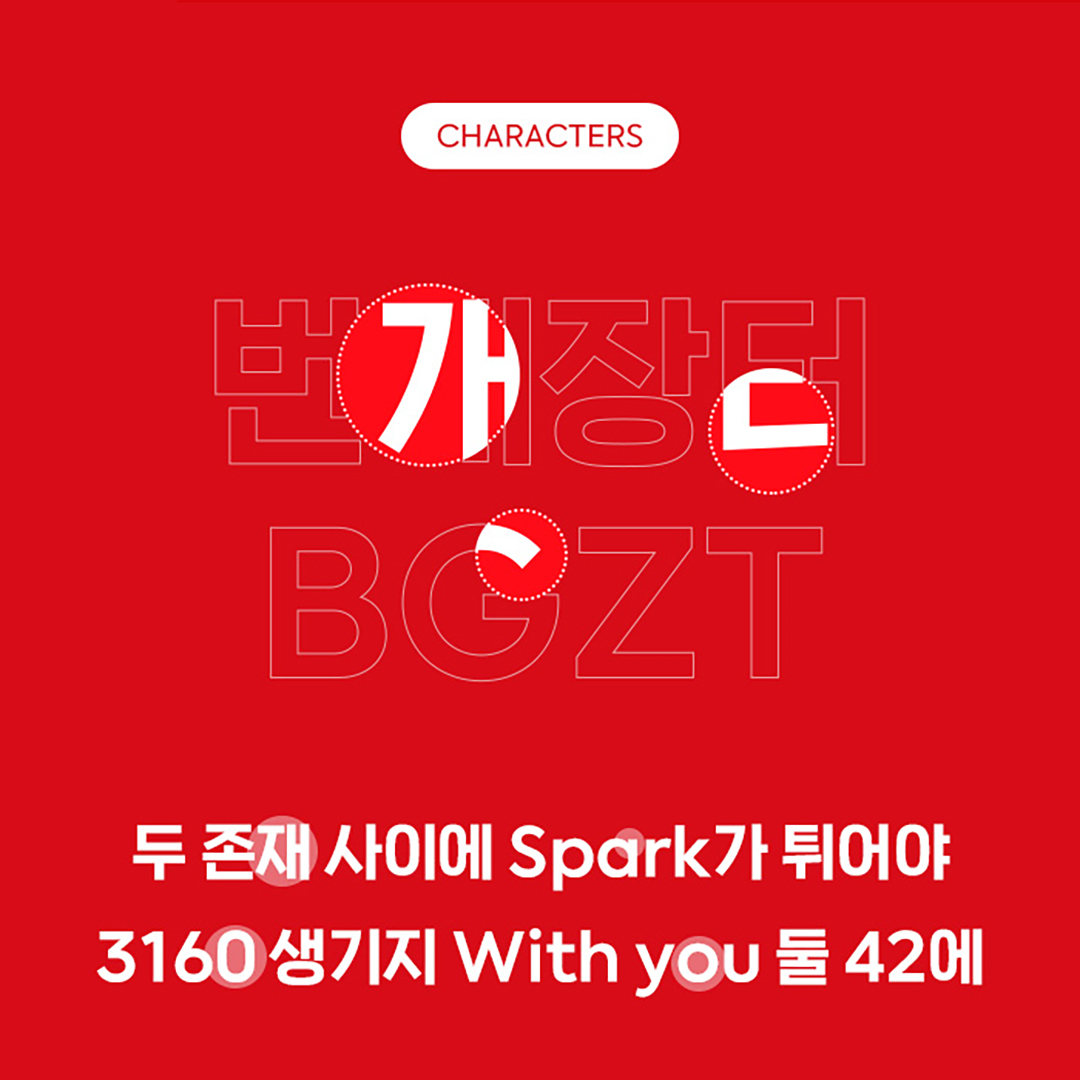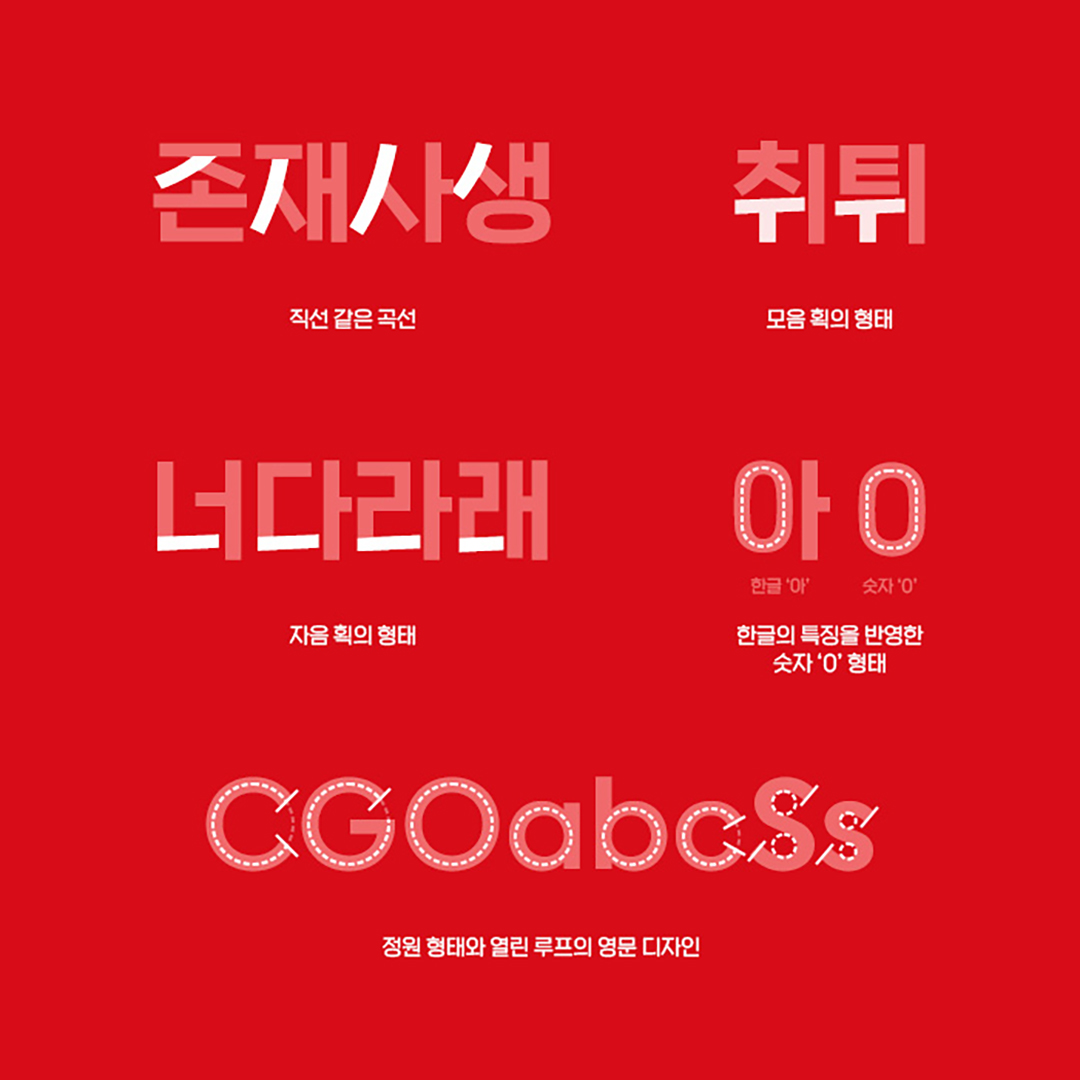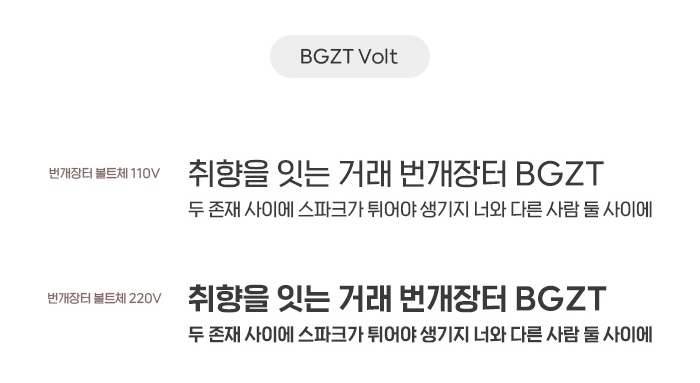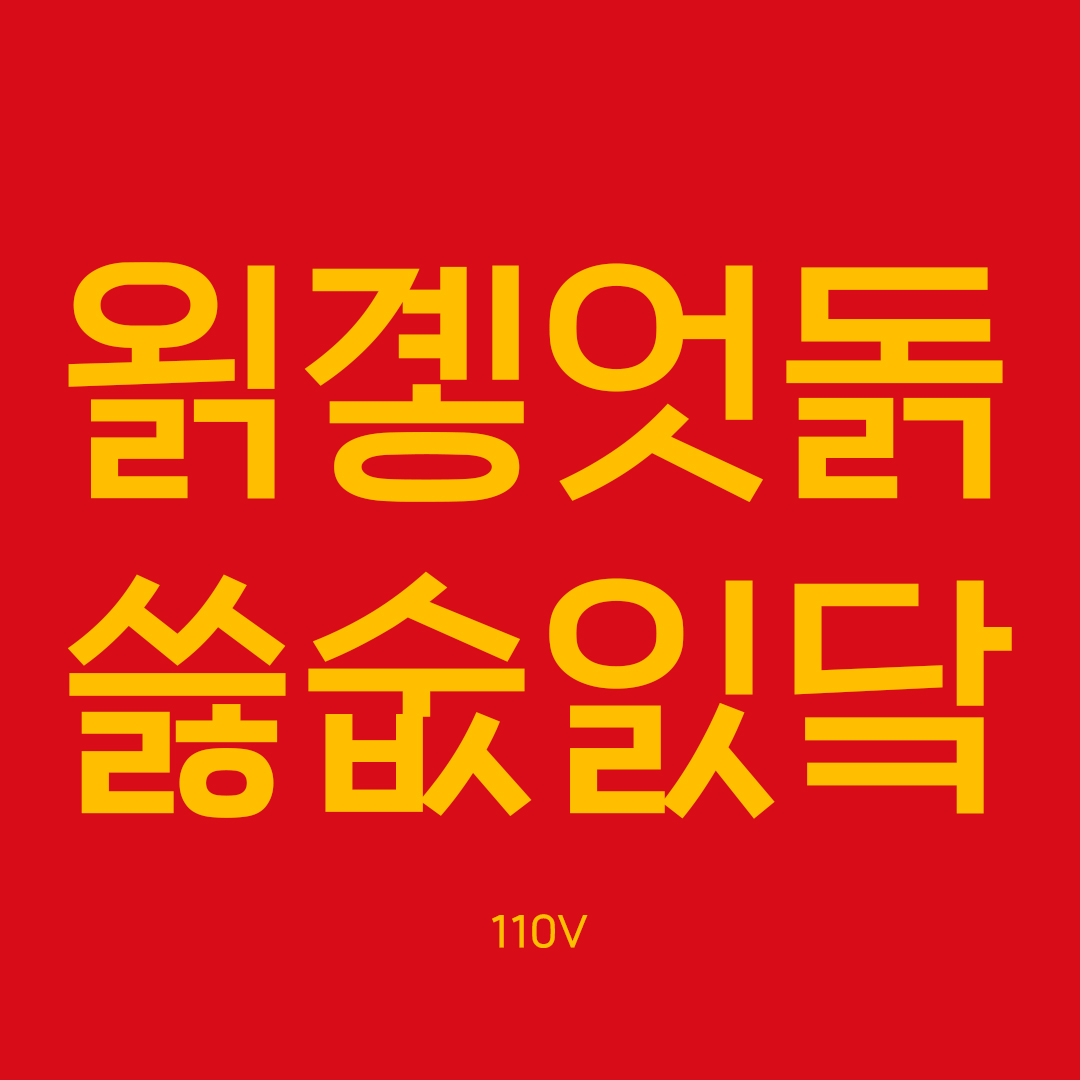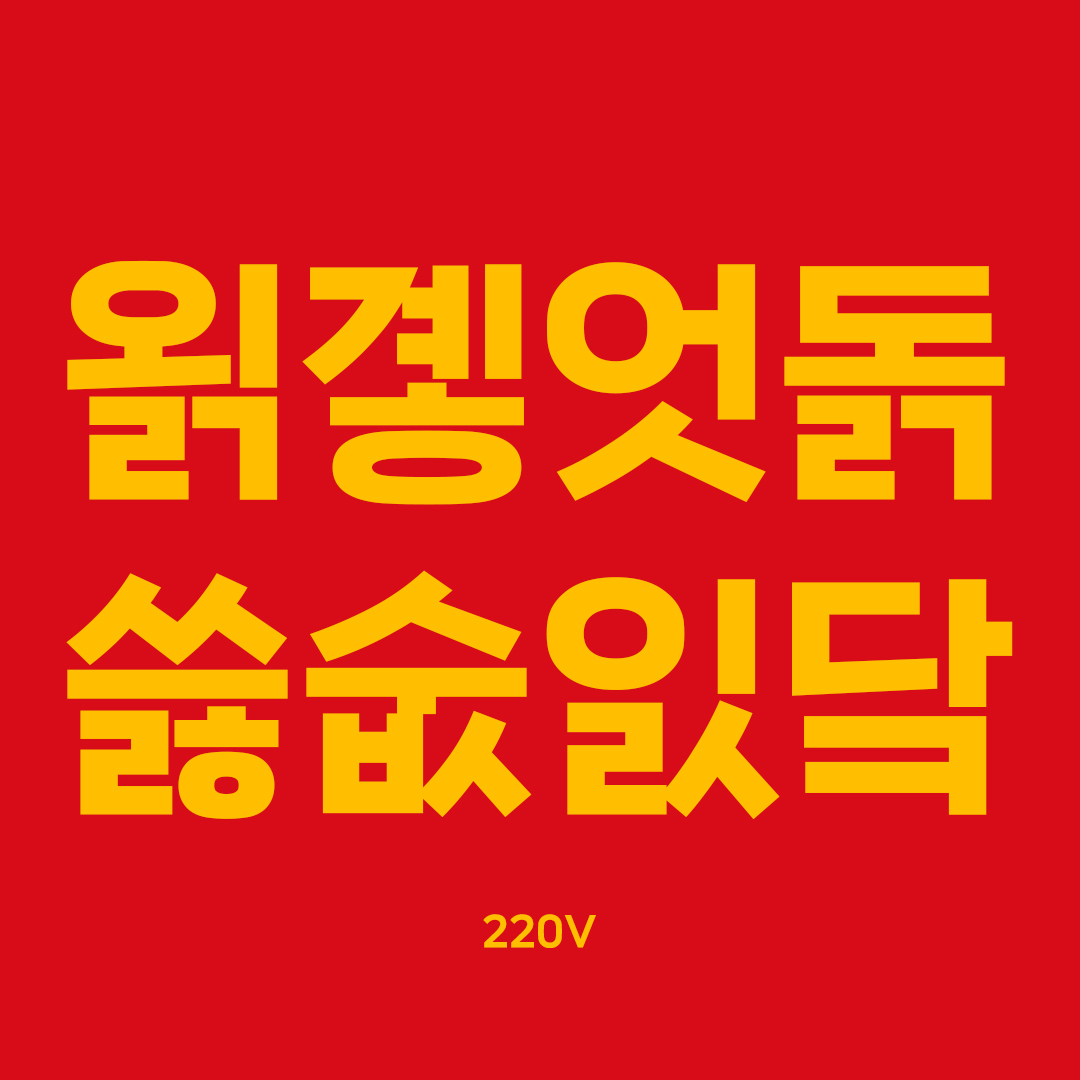
안녕하세요. 오늘은 대표적인 중고거래 플랫폼 중 하나인 번개장터의 전용서체 「볼트체」를 소개해 드려요! 서체명부터 전기가 찌릿찌릿 강렬한 개성 넘치는 서체가 탄생한 느낌이 드는데요. 취향을 기반으로 하는 안전한 중고거래 플랫폼에 대한 비전을 담아 제작한 번개장터 볼트체에 대해 자세히 알아볼게요!
#1 취향의 스파크가 튀는 볼트체 ⚡
전용서체 제작 시 가장 중요한 작업 중 하나가 바로 기업의 이미지와 아이덴티티를 담는 것인데요. 기업의 브랜딩에 큰 역할을 하는 서체 개발인 만큼 많은 커뮤니케이션과 연구가 필요한 부분이죠. 번개장터는 중고거래 플랫폼으로 독특하게 취향에 대한 이야기를 하는 브랜드예요. 서로 다른 두 가지의 취향이 만나 스파크가 튀어야 거래가 이뤄질 수 있다는 의미를 담은 새로운 로고에 맞춰 볼트체를 개발했습니다.
번개장터의 번개같이 빠른 거래, 취향의 스파크 등 키워드를 녹여내기 위해 주로 직선적인 요소를 많이 사용하여 시원한 분위기의 트렌디한 디자인의 서체를 제작했습니다. 꽉 찬 네모꼴 형태에 단단하고 안정감을 주는 구조로 빠르지만 안전한 중고거래 플랫폼의 이미지를 담았습니다. 한글의 특징을 반영하여 함께 사용할 때 조화로운 영문, 숫자, 심볼 등의 디자인도 신경 써서 제작했습니다.
#2 위트와 재미를 담은 폰트
위트 있고 자신감 넘치는 번개장터의 성격을 담은 볼트체라는 이름에 맞게 두께 표기도 좀 더 특별하게 했는데요🔌 얇은 110볼트, 두꺼운 220볼트 두 가지 굵기로 표현해 재미를 더했습니다. 110V나 220V 모두 읽기 편하도록 너무 얇거나 두껍지 않은 정도로 제작해 활용도를 높였습니다.
한글 11,172자로 개발하여 모든 한글 자소 및 각종 외계어도 출력 가능한 점도 장점 중 하나⚡
어떤 글자도 어색하지 않게 쓸 수 있고, 재밌고 다양한 표현이 가능하도록 고려하여 제작했습니다.
#3 취향 저격, 활용도 만점💯
현재 볼트체는 이미 공식 홈페이지뿐 아니라 블로그, 모바일 애플리케이션 등 다양한 환경에서 사용되고 있습니다. 번개장터 전용서체만의 특징을 잘 담고 있으면서 가독성도 좋기 때문에 큰 글씨나 작은 글씨 상관없이 활용도가 높습니다.
요즘은 아무래도 영상을 통해 콘텐츠를 접하게 되는 경우가 많은데요. TV 광고나 유튜브 등 영상 타이틀이나 자막에도 활발히 사용되고 있으며, 번개장터의 새 로고와도 잘 어우러지는 것을 볼 수 있습니다.
길을 가다 개발한 서체를 발견하면 이렇게 반가울 수 없죠❤ 오랜 시간 공들여 제작한 서체가 실제로 사용되어 일상에서 만나게 될 때 정말 반갑고도 뿌듯한 마음이 듭니다. 앞으로도 자주 볼 수 있길!
번개장터 전용서체는 제작 과정과 결과물 모두 만족스러웠던 성공적인 타이포 브랜딩 사례입니다. 디자인의 기본을 지키면서 트렌드도 놓치지 않는 기업만의 전용서체는 브랜드의 힘을 키워줍니다. 시대에 발맞춰 나아가는 감각적인 디자인과 이를 뒷받침할 단단한 기술력으로 성공적인 타이포 브랜딩을 구축합니다.